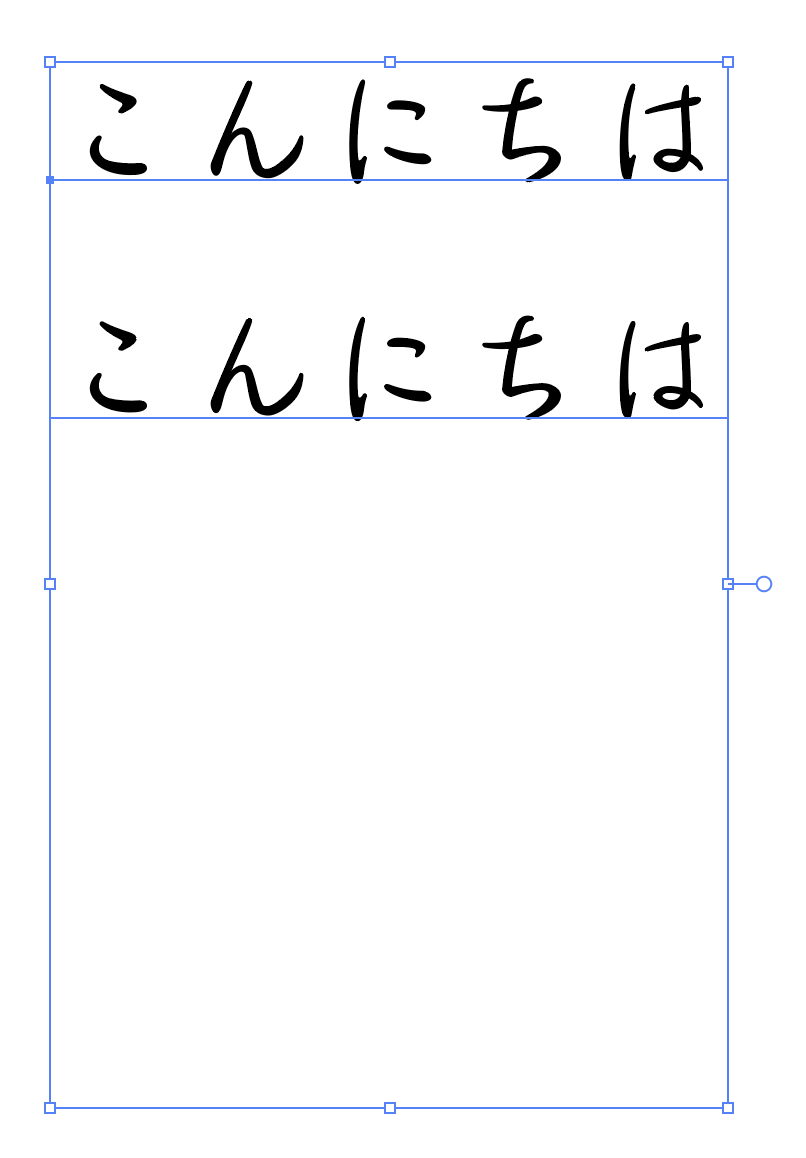
【みちくさについて】
みちくさの特徴
みちくさはAdobe-Japan1-3の文字セットをサポートしますが、それ以外にも約1,000の連綿体や代替字形が用意されており、OpenType機能を使用して、縦組みの際に文脈を考慮した連綿体(合字)などを呼び出すことができます。
連綿体(合字)とは
みちくさは、特定の品詞において、手書きの続け字から着想を得た縦書き用の連綿体が用意されています。
この連綿体を合字機能(複数の文字を合成して1文字に置換する機能)を活用し表現しています。
連綿体による文脈考慮の例1(始筆・脈略・終筆)
みちくさの連綿体(合字)には、2文字から5文字までの様々な形を持ちます。
また、各合字の多くは、基本のデザインに加えて、始筆、脈絡、終筆用にそれぞれ異なるデザインのバリエーションが用意されています。
始筆の合字は、文章の始まりで使用するためのもので、その合字の次に来る文字への繋がりを意識してデザインされています。
脈絡の合字は、文章の途中で使用するために、前後に来る文字との繋がりを考慮したデザインになっています。
終筆の合字は文末用で、その直前に来る文字との繋がりを意識してデザインされています。
後述する「デザインのセット1 :自動的に連綿を有効にする」を選択すると、文脈によってそれぞれ最適な合字の種類を自動で呼び出します。
連綿体による文脈考慮の例2(連続する合字の打ち消し)
文脈を考慮するさまざまな機能の中でも、みちくさは連綿体の連なりを禁止する機能を搭載しています。
連綿体が文章内で連続して登場してしまうと、煩雑な印象や読みづらさを招きかねません。そこで、「デザインのセット1 :自動的に連綿を有効にする」を選択すると、文脈に依存した連綿体を自動的に呼び出し、最も自然な連綿体の文章をつくることができます。
「など」「ある」「らしい」と連綿体が3つ続く場合、「デザインのセット1」を選択することで、真ん中の「ある」の連綿体が自動的に解除され、自然な連綿体の文章をつくる。
連綿体等の代替字形を呼び出すには(デザインのセットの適応)
みちくさが保有する連綿体などの代替字形は、OpenType機能 デザインのセット、およびデザインのバリエーションを使用して発動させることができます。
・セット1:自動的に連綿を有効にする
・セット2:代替字形: ひらがな
・セット3:基本的な連綿体
・セット4:デザイン連綿体: 始筆
・セット5:デザイン連綿体: 脈絡
・セット6:デザイン連綿体: 終筆
・セット7:合字・抱き字(より・すし・はし、など)
・セット8:その他の代替字形
デザインのセットの4~6では、セットを適応する文章の文脈を判断せずに、該当するグリフを、選択した種類の連綿体合字(始筆/脈絡/終筆)に一括置換します。
デザインのセット2や7、8を使って、合字以外でもさまざまなデザインの代替字形を選ぶことができます。
代替字形の例。連綿体の合字以外にもさまざまなデザインが用意されている。
連綿体と代替字形の一覧